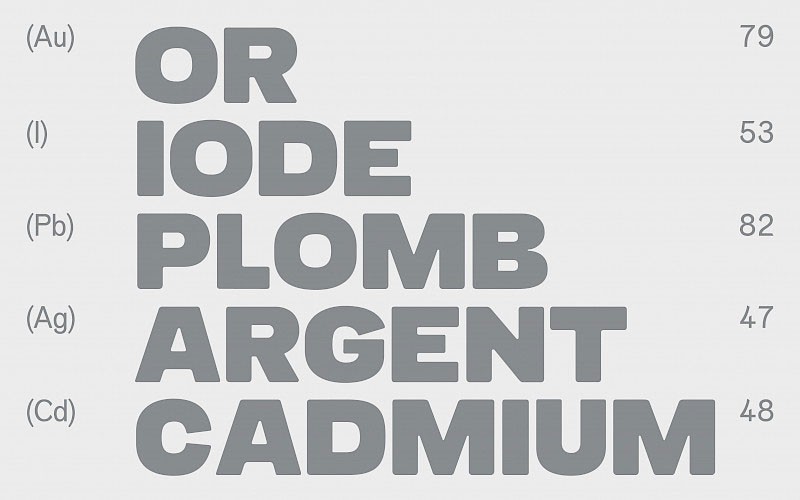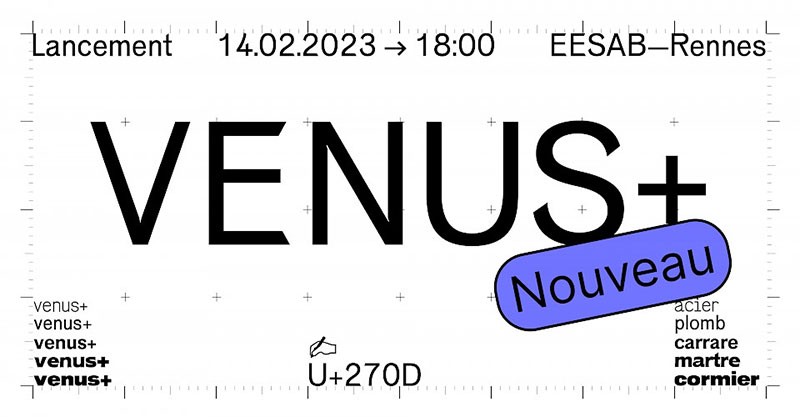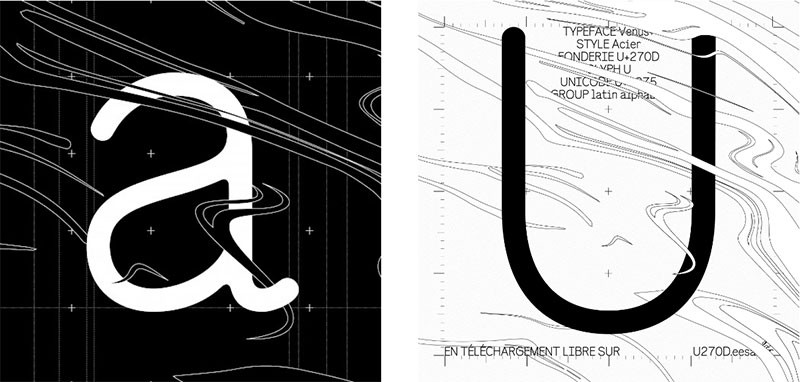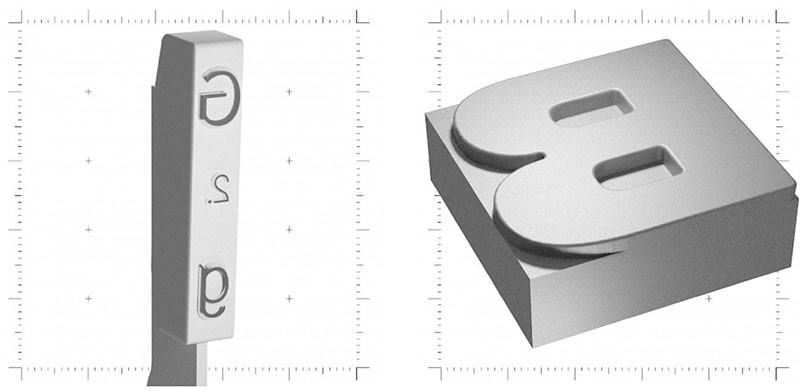
Venus+ 可商用无衬线英文字体
Venus+ 是一种无衬线字体,由美国字体设计师 John Benson 设计。它是 Venus 字体的升级版,增加了更多的字重和字符集。
Venus+ 字体系列包含多种字重,从 Extra Light 到 Ultra Black,该字体系列的设计风格简洁、现代、优美,易读且具有高度可识别性,适用于品牌、标志、标题、广告、包装、印刷品和网页设计等各种创意项目。